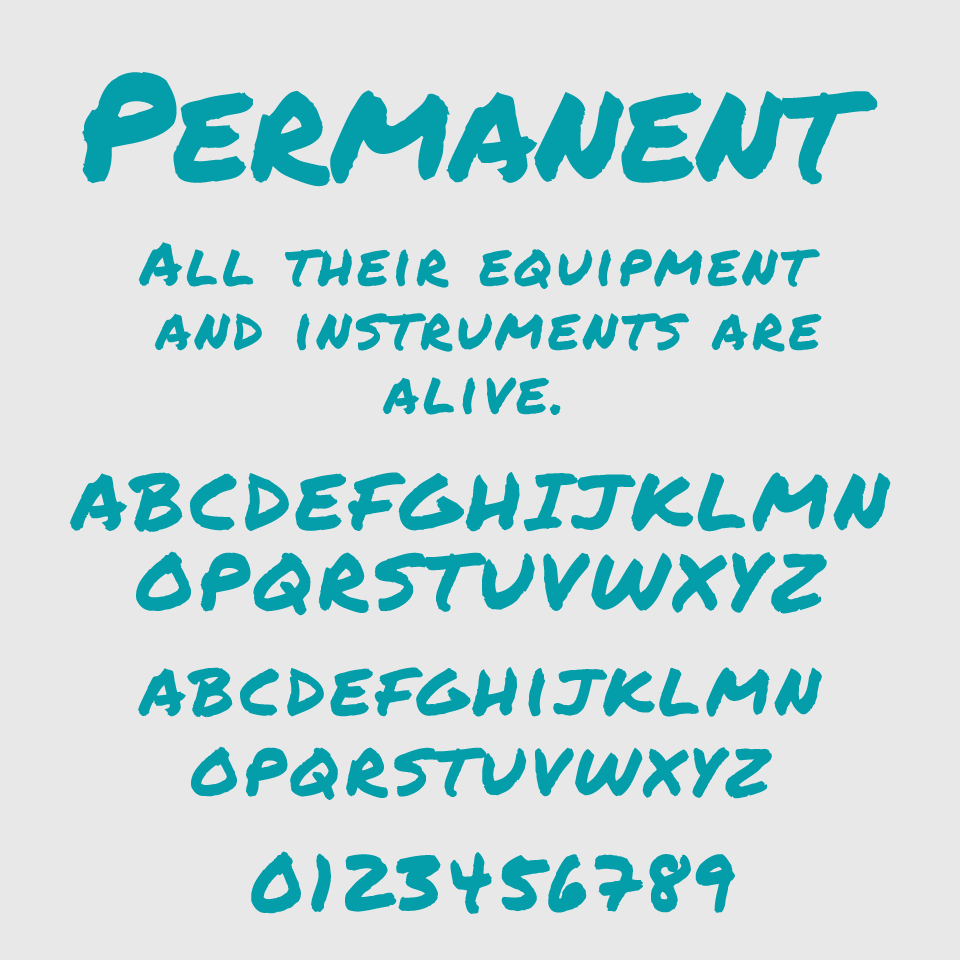
Permanent Markerフォントは、太く勢いのある筆致がストリート感がありエモさもある魅力の手書き系フォントです。
マーカーやマジックペンで一気に書いたような力強いラインと、わずかな掠れがリアルなラフさを表現しています。
イベントポスターやカジュアルなブランドロゴ、ストリート系の表現などに向いており、遊び心とインパクトを求めるシーンにおすすめです。